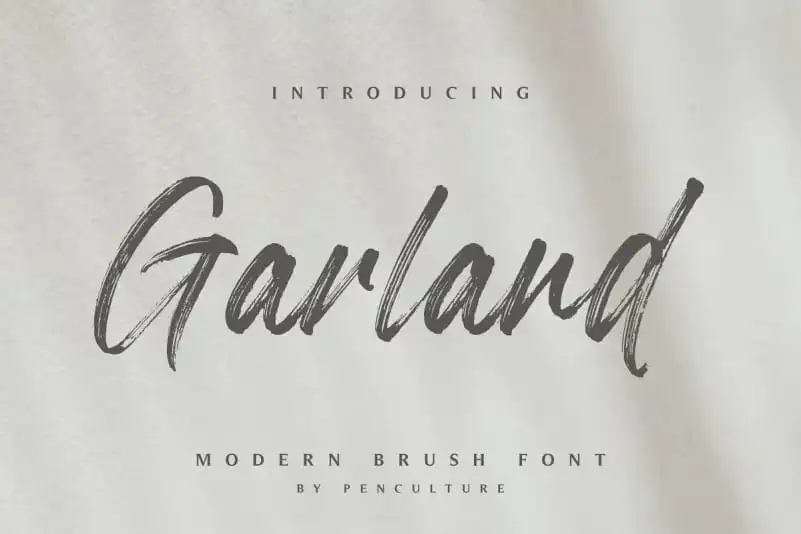
Garland Brush Font – Download Grátis
A Garland Brush Font é uma escolha perfeita para aqueles buscando adicionar um toque elegante e moderno aos seus projetos digitais. Inspirada no estilo das tintas de pincel tradicionais, essa fonte Hanwritten oferece uma textura de pincel distintiva e profunda, criada por Pen Culture. Seu traço suave e fluido encaixa-se perfeitamente para criar logos, artefatos publicitários, embalagens de produtos, e muito mais. Com suas linhas naturais e únicas, a Garland Brush Font surge como uma fonte script versátil que se destaca no mercado. Seja você um criador de logotipos profissional ou simplesmente alguém que deseja dar um toque único em sua próxima arte digital, essa fonte é certamente o item de equipamento que você precisa.